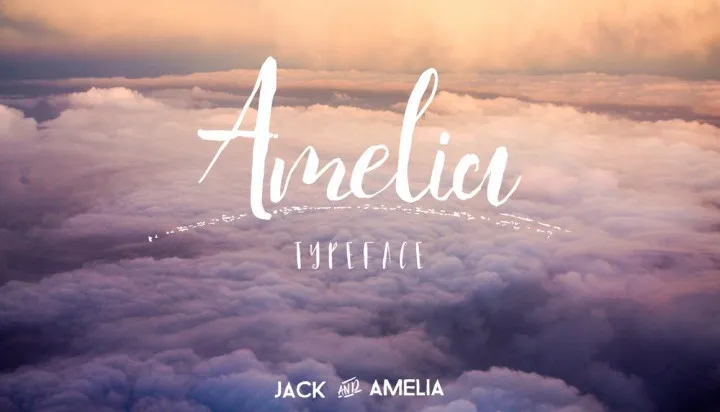
Introduzimos a Amelia Script Font! Desenhada pelo designer Efe Gürsoy, esta é uma fonte premium, disponível para download gratuito no Creativemarket hoje. Amelia é um novo tipo de caligrafia criado por mãos humanas. É perfeitamente adequada para design e identidades visuais que abordem temas como temáticas de águacolor, vintage e retro. Excelente para criações de convites ou cards de agradecimento com temas de águacolor. Além disso, também se aplica a designs web, publicitários e até mesmo convites de casamento. O seu uso é vasto em várias áreas, incluindo impressão, design para roupas, web e identidade visual do casal. Com a Amelia Script Font, você terá o prazer de experimentar um tipo único que vai dar ao seu trabalho um toque elegante e singular. Ela oferece uma variedade de opções e personalizações para atender às suas necessidades específicas. Seja em uma festa de casamento ou no design da sua própria identidade visual, a Amelia Script é certamente um item indispensável do seu arsenal de fontes.